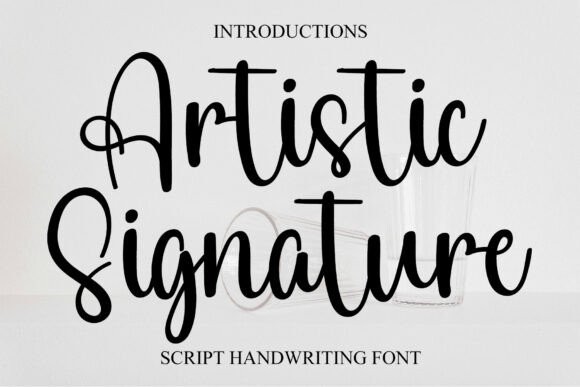
Artistic Signature
Encontrar os elementos de design certos pode ser um desafio, mas Artistic Signature oferece uma coleção excepcional que eleva o seu trabalho instantaneamente.
Trabalhado com precisão, Artistic Signature fornece vetores limpos, tipografia suave e uma licença comercial para sua tranquilidade.